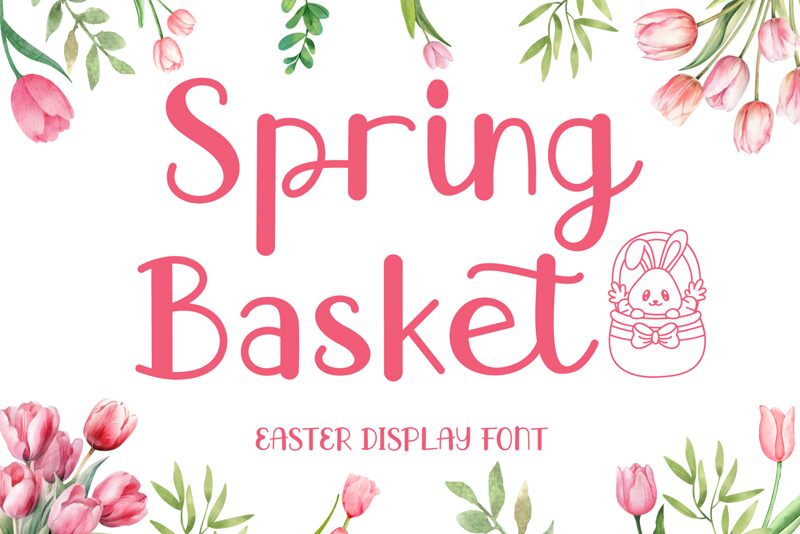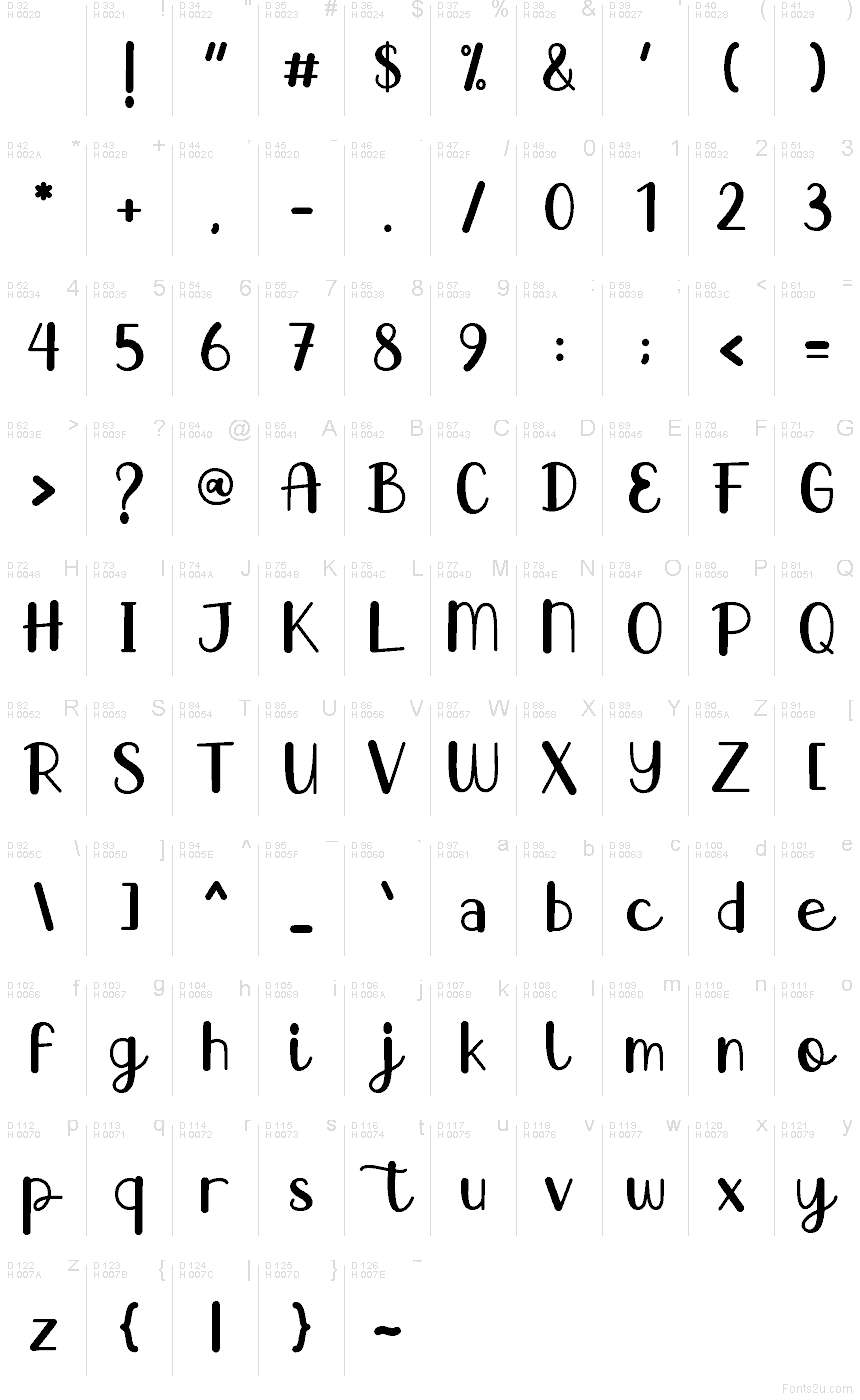
Spring Basket
La police Spring Basket, créée par AEN Creative Studio, est une typographie de Pâques gratuite aux tracés doux et arrondis, évoquant l'écriture manuscrite. Ses lettres s'enchaînent avec fluidité, marquées par un S tout en boucles, un « a » simple à un seul étage, ainsi que de petits points circulaires et des courbes qui lui donnent un aspect saisonnier et convivial.
Spring Basket est idéale pour vos invitations de Pâques, affiches de printemps, cartes de vœux, titres de scrapbooking, étiquettes de pâtisserie et emballages saisonniers. Ses formes douces et connectées apportent une touche artisanale à vos textes courts et mots décoratifs, parfaite pour une ambiance festive sans jamais paraître surchargée.